18 Font Konstruksi Terbaik ️ 2023 (Gratis & Premium)
Diterbitkan: 2023-11-28Apakah Anda pernah kesulitan menemukan font sempurna yang menyampaikan pesan yang tepat untuk proyek konstruksi Anda? Apakah Anda bosan menggunakan font lama yang tidak cukup menangkap esensi desain Anda?
Nah, jangan mencari lagi! Dalam postingan blog ini, kita akan menjelajahi font konstruksi terbaik yang akan membawa proyek Anda ke level berikutnya.
Dalam hal desain, font yang tepat dapat membuat perbedaan besar. Hal ini dapat membangkitkan rasa kekuatan, stabilitas, dan profesionalisme. Dan dalam dunia konstruksi, kualitas-kualitas ini sangat penting.
Tahukah Anda bahwa penggunaan font yang tepat dapat meningkatkan keterbacaan desain Anda hingga 27%? Itu adalah peningkatan signifikan yang dapat meningkatkan dampak pekerjaan Anda secara signifikan.
Pada artikel ini, kita akan mendalami dunia font konstruksi, mendiskusikan karakteristik uniknya dan bagaimana font tersebut dapat meningkatkan proyek Anda. Kami akan mengeksplorasi font yang tebal, bersih, dan mudah dibaca, menjadikannya sempurna untuk logo, papan tanda, dan materi promosi.
Jadi, apakah Anda sedang mengerjakan branding perusahaan konstruksi atau membuat desain yang menarik secara visual untuk rencana arsitektur, kami siap membantu Anda. Mari kita mulai mencari font konstruksi terbaik!
Font Konstruksi Premium Terbaik
Ingin meningkatkan desain proyek konstruksi Anda? Lihat saja pilihan font konstruksi premium terbaik kami yang telah dikuratori dengan cermat.
Bersiaplah untuk menambahkan sentuhan kecanggihan dan profesionalisme pada kreasi Anda. Selami untuk menemukan font yang sempurna untuk proyek Anda berikutnya!
Dalam masa pembangunan
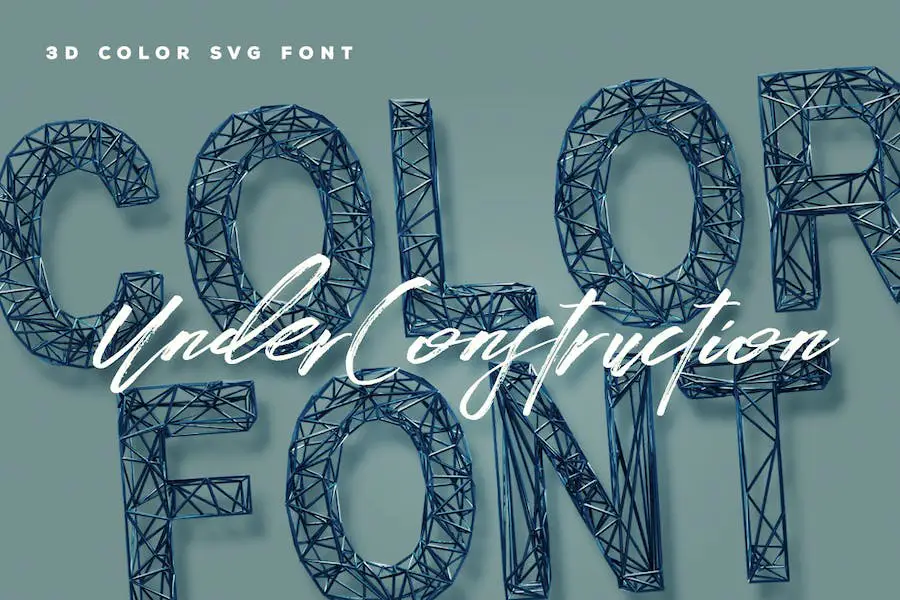
Under Construction adalah font unik dan serbaguna yang dirancang khusus untuk desainer grafis yang mengerjakan proyek terkait konstruksi. Font ini, tersedia dalam format warna dan tipe terbuka SVG, menambahkan sentuhan dinamis dan modern pada desain apa pun.
Dengan bentuk hurufnya yang berani dan menarik perhatian, Under Construction sangat cocok untuk membuat headline, logo, dan signage yang menarik perhatian.
Font ini memberikan kesan kekuatan dan soliditas pada desain Anda, benar-benar menangkap esensi industri konstruksi. Fleksibilitasnya memungkinkannya digunakan dalam berbagai konteks, menjadikannya aset berharga bagi desainer mana pun yang membutuhkan opsi font yang menonjol.
Tukang blok
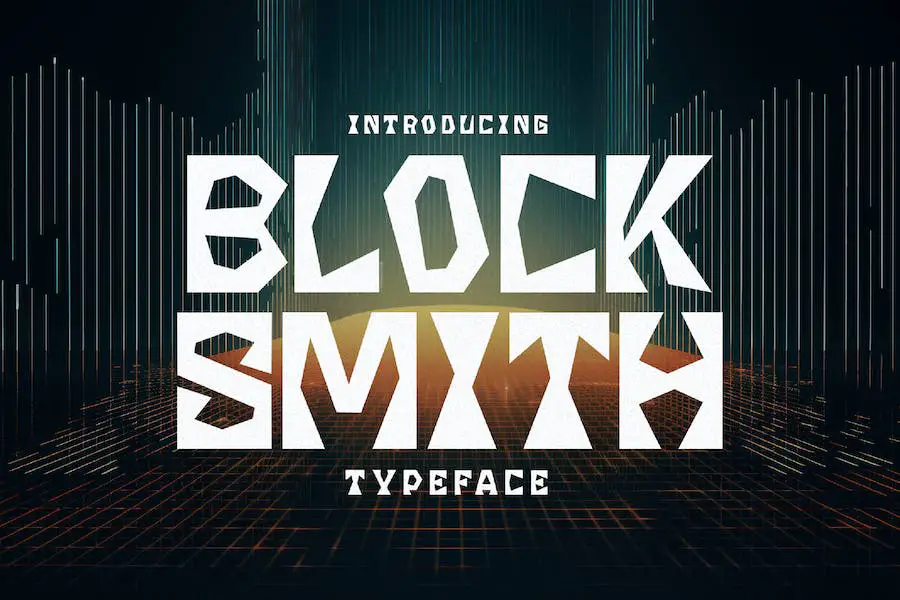
Blocksmith adalah font terbaik untuk desainer grafis yang ingin menyempurnakan desain proyek mereka. Dengan karakteristiknya yang berani dan kokoh, font ini menonjol di dunia tipografi. Ini memberikan kesan kekuatan dan dampak pada proyek apa pun yang digunakannya.
Bentuk Blocksmith yang bersih dan geometris membuatnya sempurna untuk desain bertema konstruksi. Goresannya yang berani dan strukturnya yang kokoh memancarkan kepercayaan diri dan profesionalisme, yang langsung menarik perhatian pemirsa.
Baik itu logo, situs web, atau signage, font ini menambahkan sentuhan kekuatan dan otoritas.
Selain dampak visualnya, Blocksmith sangat serbaguna. Ini dapat dengan mudah ditingkatkan atau diturunkan tanpa kehilangan kejelasannya, memastikan tampilannya bagus pada aplikasi besar dan kecil.
Konstruksi baja
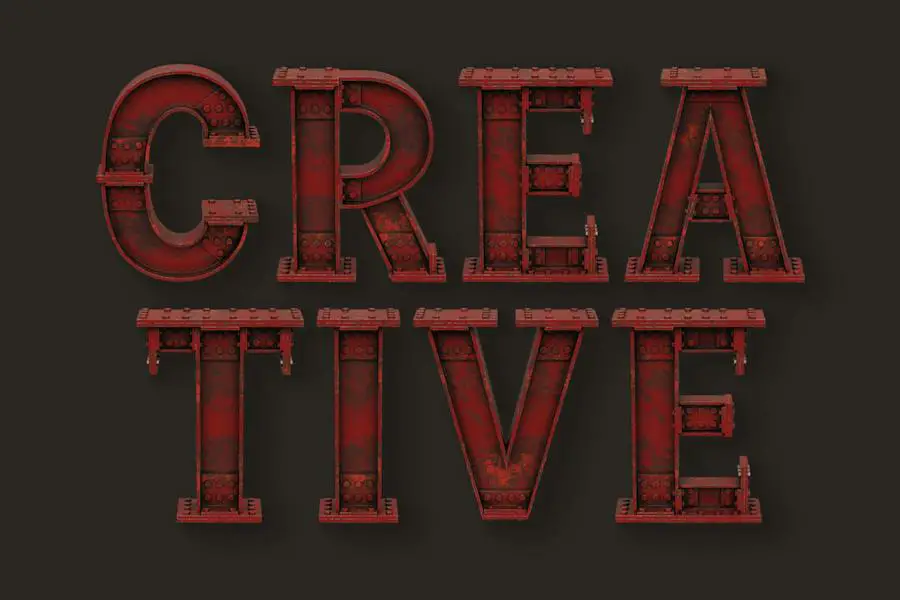
Konstruksi Baja adalah font serbaguna yang menawarkan opsi warna dan tipe terbuka SVG. Dengan desainnya yang berani dan industrial, font ini sangat cocok untuk desainer grafis yang mencari font yang akan menyempurnakan desain proyek mereka.
Atribut font ini mencakup warnanya yang menarik dan garis-garis yang tajam, menjadikannya pilihan yang sangat baik untuk pekerjaan desain yang berhubungan dengan konstruksi. Baik Anda membuat logo, brosur, atau situs web, Konstruksi Baja pasti akan menambah sentuhan profesionalisme dan gaya pada proyek Anda.
Dengan perpaduan unik antara estetika dan fungsionalitas, font ini wajib dimiliki oleh setiap desainer yang ingin tampil menonjol.
Dalam masa pembangunan
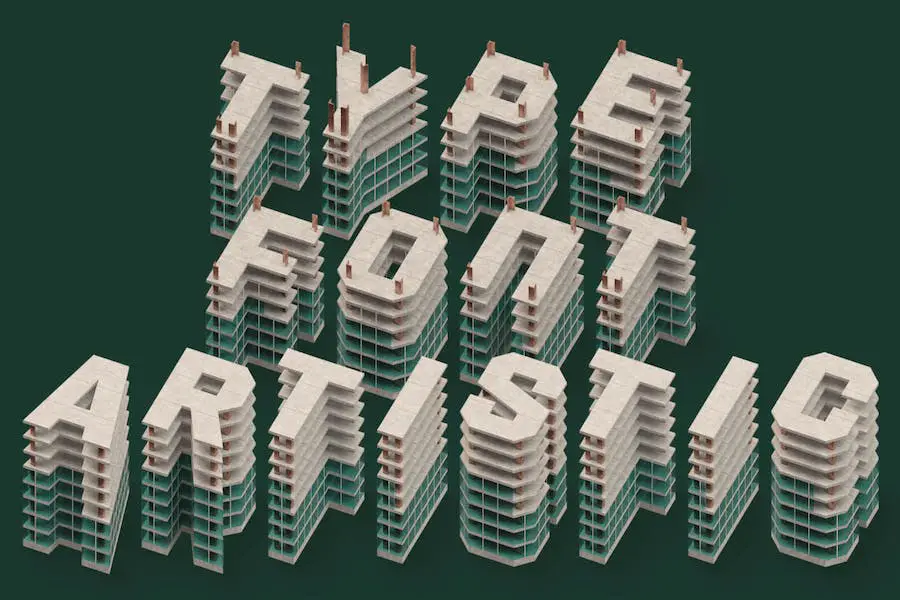
Under Construction adalah font unik dan serbaguna yang menambahkan sentuhan kreativitas dan gaya pada proyek desain grafis apa pun. Dengan huruf tebal dan menarik perhatian, font tipe terbuka berwarna atau SVG ini sempurna untuk menyampaikan kesan kekuatan dan inovasi.
Baik Anda sedang mengerjakan logo, desain situs web, atau proyek visual lainnya, Under Construction pasti akan meningkatkan kualitas pekerjaan Anda dan menarik perhatian audiens Anda.
Atribut font inilah yang membedakannya dari opsi lain di luar sana. Warnanya yang cerah dan format tipe terbuka SVG yang dinamis memungkinkan pengalaman yang benar-benar imersif dan mencolok secara visual.
Setiap huruf dirancang dengan cermat agar menyerupai berbagai elemen konstruksi, seperti balok, baut, dan perancah, menciptakan kesan bangunan dan kemajuan.
Metrisch
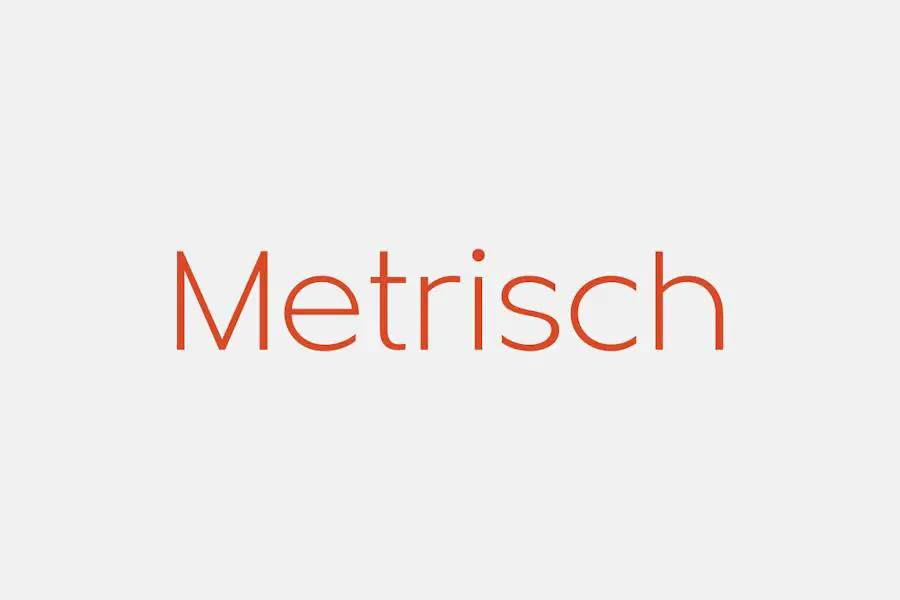
Metrisch adalah keluarga tipe sans serif modern yang menawarkan total tujuh bobot dan huruf miring yang sesuai di setiap bobot. Font serbaguna ini sangat cocok untuk desainer grafis yang ingin menyempurnakan proyek mereka dengan sentuhan ramping dan kontemporer.
Dengan garis-garisnya yang bersih dan tampilannya yang canggih, Metrisch menghadirkan kesan profesionalisme dan keanggunan pada desain apa pun. Ini menawarkan berbagai bobot, memungkinkan desainer untuk menciptakan kontras dan hierarki yang menarik dalam tipografi mereka.
Baik Anda sedang mengerjakan logo, situs web, atau materi cetak, Metrisch siap membantu Anda. Variasi bobot dan huruf miringnya memberi Anda fleksibilitas untuk bereksperimen dan menemukan keseimbangan sempurna untuk desain Anda.
Pasca-beban
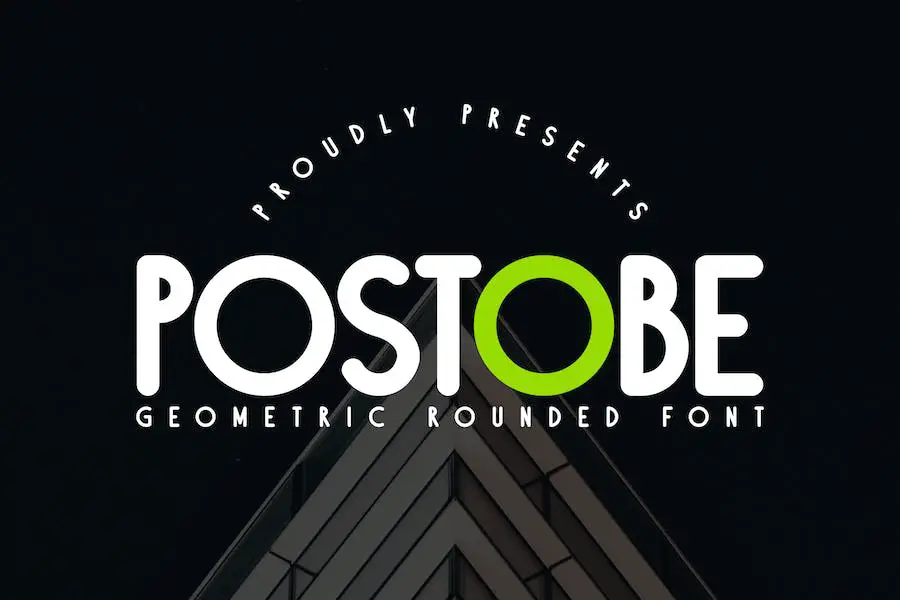
Postobe adalah font serbaguna yang menawarkan berbagai ukuran dan gaya untuk desainer grafis. Dalam koleksi mesin terbangnya, Anda akan menemukan variasi tinggi dan lebar, memungkinkan fleksibilitas desain yang lebih besar. Dengan tiga ukuran berbeda untuk dipilih, Postobe meningkatkan estetika keseluruhan proyek apa pun.
Fitur unik Postobe terletak pada ukuran mesin terbangnya yang disesuaikan. Beberapa mesin terbang sengaja dibuat lebih pendek, sementara yang lain mempertahankan ketinggian standar. Selain itu, mesin terbang tertentu lebih lebar, menambahkan sentuhan dinamis pada tipografi Anda.
Variasi ini memberikan kesempatan bagi desainer untuk bereksperimen dan menciptakan desain visual yang menawan.
Perak Emas
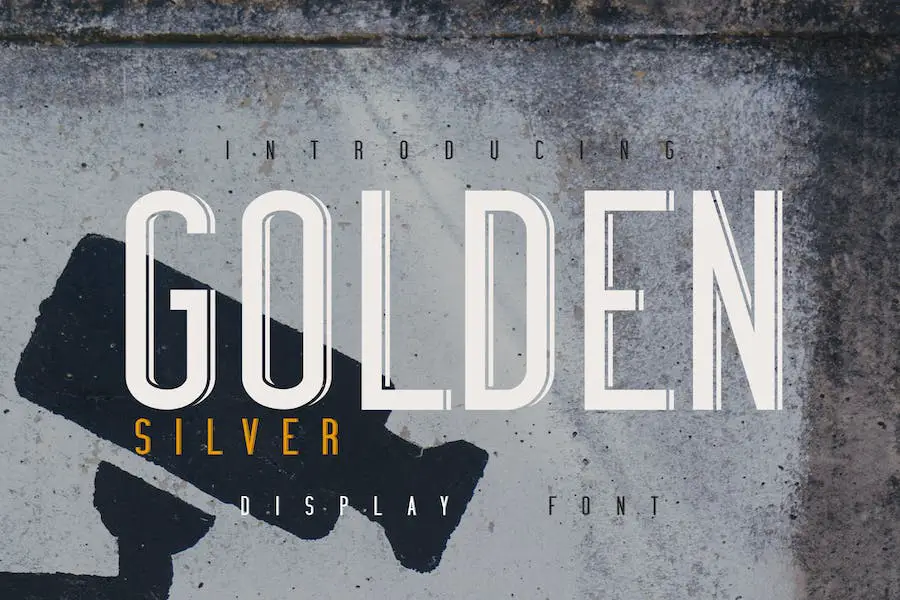
Golden Silver adalah font yang menghadirkan sentuhan keanggunan dan kecanggihan pada setiap proyek desain grafis. Didesain khusus dengan mempertimbangkan konstruksi dan pekerjaan berat, font ini berani dan berani, sama seperti industri yang diwakilinya.
Salah satu fitur menonjolnya adalah sisi khusus seperti bayangan dalam jajaran karakternya, menambahkan elemen unik dan menarik pada desain Anda.
Dengan Golden Silver, Anda dapat langsung meningkatkan proyek Anda dengan memberikan kesan halus dan profesional.
Baik Anda membuat logo untuk perusahaan konstruksi atau merancang materi promosi untuk merek alat berat, font ini pasti akan memberikan kesan mendalam. Penampilannya yang berani dan berwibawa menuntut perhatian serta memancarkan rasa kekuatan dan keandalan.
Teroksia Pro
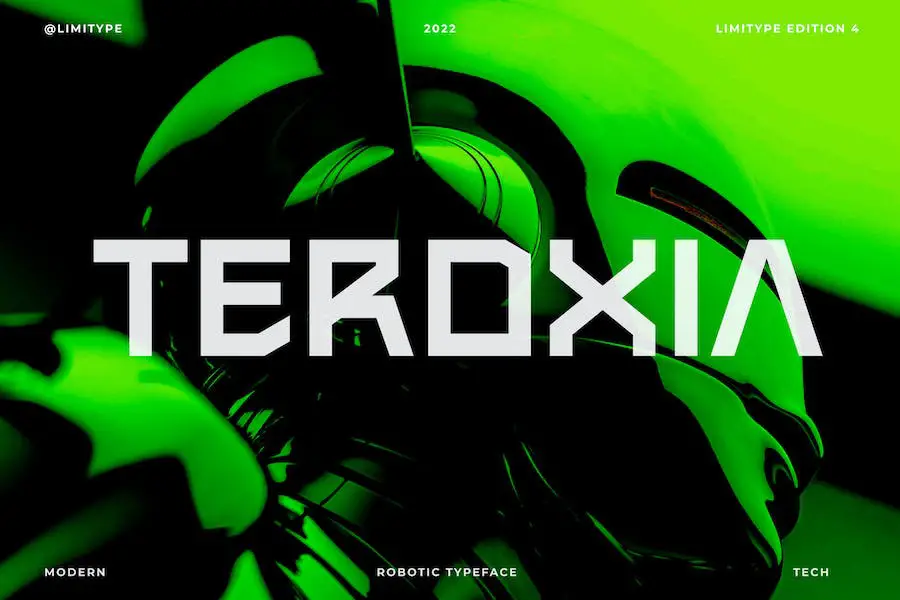
Teroxia Pro adalah jenis huruf unik yang mengambil inspirasi dari bentuk ramping dan kuat yang ditemukan pada robot dan mesin.
Dengan desainnya yang modern dan futuristik, ia menambahkan sentuhan kecanggihan pada setiap proyek desain grafis. Bentuk Teroxia Pro yang tajam dan berani memikat mata dan meningkatkan daya tarik visual secara keseluruhan.
Lengkungan dan konstruksinya yang dibuat dengan cermat menjadikannya font serbaguna yang dapat digunakan untuk berbagai tujuan. Baik Anda sedang mengerjakan logo, poster, atau situs web, Teroxia Pro pasti akan meningkatkan desain ke tingkat yang lebih tinggi.
Astronom
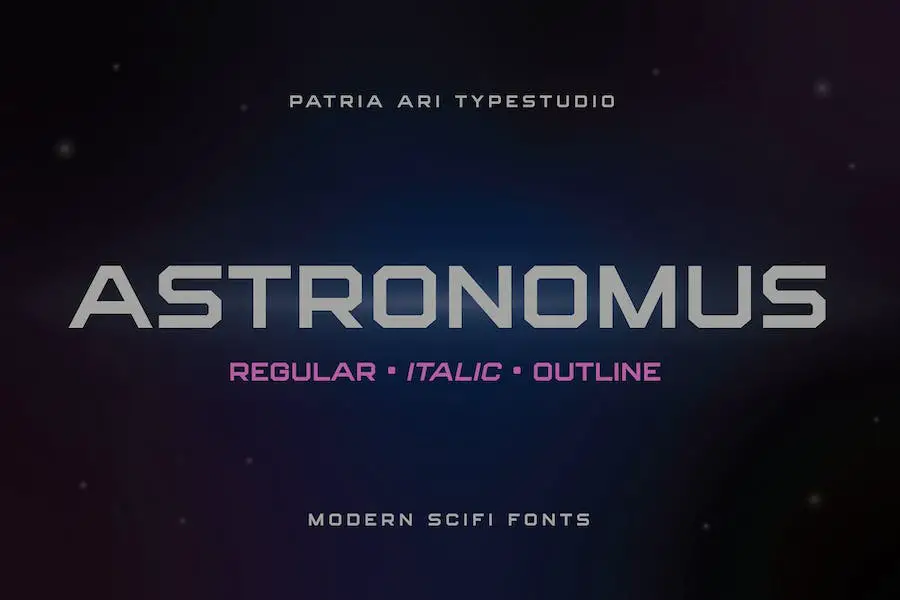
Astronomus adalah font modern berteknologi fiksi ilmiah yang menghadirkan sentuhan futuristik pada desain Anda. Dengan bentuk dan gayanya yang unik, font ini membedakannya dari font tradisional.
Huruf besar dan kecil di Astronomus memiliki variasi yang khas, sehingga menambah unsur kreativitas pada proyek Anda. Tampilannya yang ramping dan modern membuatnya sempurna untuk desain bertema fiksi ilmiah atau teknologi, memberikan kesan mutakhir.
Baik Anda mendesain logo, membuat poster, atau mengerjakan situs web, Astronomus akan membantu meningkatkan proyek Anda dan membuatnya menonjol dari yang lain. Nuansa fiksi ilmiahnya menambah kesan kecanggihan dan futurisme pada desain apa pun.
potongan jalur
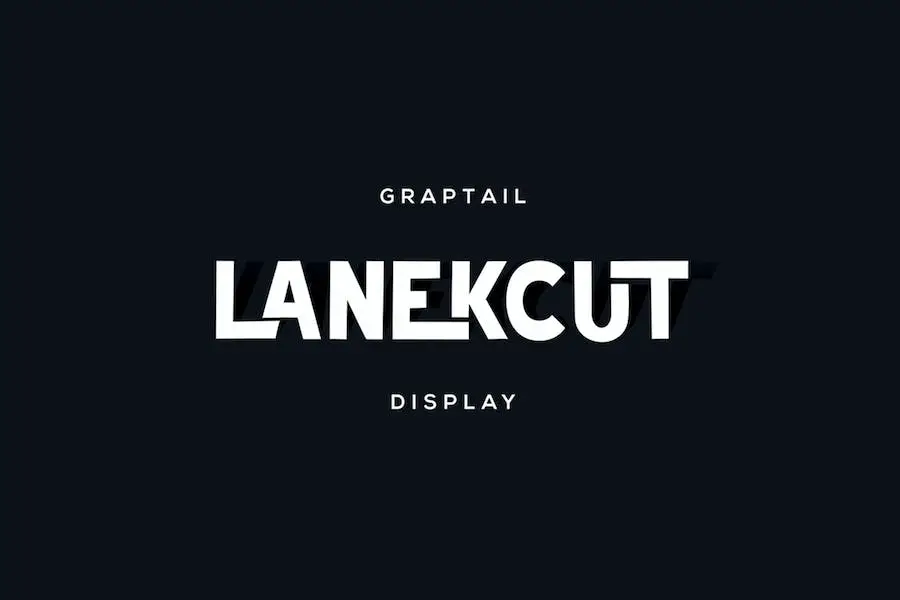
Lanekcut adalah font pengikat yang menggabungkan karakter dan fungsionalitas dengan cara yang unik. Dengan konsep font pengikat, ini memberikan sentuhan khas pada proyek desain apa pun.
Salah satu atribut yang menonjol dari Lanekcut adalah kemampuannya memancarkan karakter. Font ini memiliki kepribadian yang berbeda dan menambahkan sentuhan gaya pada desain apa pun. Baik Anda sedang mengerjakan logo, situs web, atau kemasan, Lanekcut akan membantu menciptakan tampilan yang berkesan dan menarik.
Tapi Lanekcut tidak mengorbankan kegunaan demi gaya. Ini tetap praktis dan mudah dibaca, memastikan pesan Anda tersampaikan secara efektif. Font ini memberikan keseimbangan sempurna antara kreativitas dan fungsionalitas, menjadikannya pilihan serbaguna bagi desainer grafis.
Robinso
Robinson adalah font yang sangat serbaguna yang dapat menyempurnakan desain proyek Anda. Baik Anda sedang mengerjakan branding, kartu nama, poster, logo, majalah, sampul, spanduk, kaos oblong, header, atau bahkan karya seni berskala besar, font ini sangat cocok untuk penggunaan cetak dan layar.
Dengan estetika bersih dan modern, Robinso menambahkan sentuhan kecanggihan pada desain apa pun. Bentuk hurufnya yang ramping dan penuh gaya menciptakan dampak visual yang kuat, membuat teks Anda menonjol dan menarik perhatian. Font ini sangat cocok untuk proyek yang membutuhkan tampilan profesional dan halus.
Salah satu fitur menonjol dari Robinso adalah keterbacaannya yang luar biasa. Setiap huruf dibuat dengan cermat untuk memastikan keterbacaan, bahkan pada ukuran yang lebih kecil. Hal ini menjadikannya ideal untuk proyek di mana Anda perlu menyampaikan informasi dengan jelas dan efektif.
Baik Anda mendesain tata letak majalah atau logo, Robinson akan memastikan pesan Anda mudah dipahami.
Musim panas
Musim panas adalah font tulisan tangan yang menyenangkan dengan konstruksi kokoh yang menambahkan sentuhan pesona pada proyek desain apa pun. Atribut uniknya menjadikannya suatu keharusan bagi desainer grafis yang ingin menyempurnakan proyek mereka.
Dengan Musim Panas, Anda mendapatkan yang terbaik dari kedua dunia: tampilan tulisan tangan dipadukan dengan fondasi yang kokoh. Konstruksinya yang kokoh memberikan kekuatan dan stabilitas pada font, menjadikannya sempurna untuk menyampaikan rasa keandalan dan profesionalisme.
Font ini memancarkan kesan keaslian, seolah-olah ditulis dengan tangan dengan hati-hati dan memperhatikan detail. Garis-garisnya yang halus dan proporsinya yang seimbang membuatnya enak dipandang, sementara konstruksinya yang kuat memastikan keterbacaan dalam berbagai ukuran dan konteks.
Font Konstruksi Gratis Terbaik
Ingin menambahkan sentuhan ekstra kreativitas pada proyek konstruksi Anda? Lihat pilihan font konstruksi gratis terbaik kami. Font ini tidak hanya menarik secara visual tetapi juga sangat serbaguna, memungkinkan Anda meningkatkan desain Anda ke tingkat yang lebih tinggi.
Jangan lewatkan kesempatan ini untuk menyempurnakan proyek Anda – lihat produk berikut di artikel ini!
Konstruksi
Konstruksi adalah font yang dirancang khusus untuk desainer grafis yang ingin menyempurnakan desain proyek mereka. Ini adalah font serbaguna dan bergaya yang dapat digunakan dalam berbagai desain terkait konstruksi.
Dengan garis-garisnya yang berani dan bersih, Konstruksi menambahkan sentuhan modern dan profesional pada proyek apa pun.
Font ini menampilkan huruf-huruf yang kuat dan solid yang memancarkan kesan kuat dan stabil. Baik Anda membuat logo untuk perusahaan konstruksi atau mendesain selebaran untuk proyek bangunan, Konstruksi adalah pilihan yang tepat.
Penampilannya yang berani dan bertenaga langsung menarik perhatian dan memberikan kesan yang kuat.
Garis Konstruksi
Construction Lines adalah font yang dibuat oleh Checkered Ink yang sempurna untuk desainer grafis yang ingin menyempurnakan desain proyek mereka. Font serbaguna ini menambahkan sentuhan unik dan profesional pada desain bertema konstruksi apa pun, menjadikannya menonjol dari pesaing.
Dengan garis-garisnya yang bersih dan tampilannya yang berani, Construction Lines cocok untuk berbagai proyek terkait konstruksi, termasuk logo, data infografis, dan iklan.
Tepian font yang tajam dan kehadiran yang kuat membuatnya menarik secara visual dan mudah dibaca, memastikan pesan Anda dikomunikasikan secara efektif kepada audiens Anda.
Atribut Garis Konstruksi benar-benar menjadikannya pilihan font yang menonjol. Bentuk hurufnya yang kokoh dan berani memberikan kesan keandalan dan kekuatan, yang secara sempurna mencerminkan esensi industri konstruksi.
Font ini juga mempertahankan estetika yang ramping dan modern, memberikan desain Anda keunggulan kontemporer.
Mekanisme
Mechanismo oleh sdotype adalah pilihan font yang fantastis untuk desainer grafis yang ingin meningkatkan desain proyek mereka. Font bertema konstruksi ini menambahkan sentuhan unik dan menghadirkan kesan kekuatan dan presisi pada desain apa pun.
Dengan bentuk huruf yang tebal dan bersudut, Mechanismo sempurna untuk membuat headline, logo, dan signage yang menarik.
Atribut Mechanismo menjadikannya pilihan yang sangat baik untuk proyek desain apa pun. Bentuknya yang berani dan geometris memberikan dampak visual yang kuat, sementara garis-garisnya yang rapi memastikan keterbacaan bahkan pada ukuran kecil.
Elemen khas yang terinspirasi dari konstruksi menambah kesan kecanggihan industri pada desain apa pun, menjadikannya pilihan sempurna untuk proyek terkait konstruksi atau desain apa pun yang bertujuan untuk memberikan kekuatan dan stabilitas.
Txuleta Deco
Txuleta Deco adalah font fantastis yang dapat menyempurnakan desain proyek konstruksi Anda. Dibuat oleh deFharo, atribut unik dan bergaya font ini menjadikannya wajib dimiliki oleh setiap desainer grafis yang ingin menambahkan sentuhan elegan pada karyanya.
Dengan Txuleta Deco, Anda akan memiliki akses ke berbagai fitur yang akan membuat desain Anda benar-benar menonjol.
Garis font yang ramping dan modern memberikan tampilan yang canggih, cocok untuk menampilkan profesionalisme dan kreativitas proyek konstruksi Anda. Desainnya yang berani dan bersih memastikan teks Anda jelas dan terbaca, bahkan pada ukuran yang lebih kecil.
Salah satu fitur menonjol dari Txuleta Deco adalah keserbagunaannya. Baik Anda sedang mengerjakan brosur, atau situs web, font ini akan beradaptasi dengan mulus pada proyek apa pun.
cepat
Fastup adalah font fantastis yang dibuat oleh deFharo yang sempurna untuk desainer grafis yang ingin menyempurnakan desain proyek mereka. Font ini memiliki tampilan ramping dan modern yang menambahkan sentuhan profesional pada desain apa pun.
Garis-garisnya yang bersih dan gayanya yang berani menjadikannya ideal untuk proyek bertema konstruksi. Dengan Fastup, Anda dapat dengan mudah membuat logo, papan tanda, dan materi promosi menarik yang menonjol dari yang lain.
Font ini menawarkan berbagai atribut yang menjadikannya wajib dimiliki oleh desainer grafis. Fleksibilitasnya memungkinkannya bekerja dengan baik dalam ukuran besar dan kecil, memastikan keterbacaan dan dampak visual dalam berbagai aplikasi.
Sifat Fastup yang berani juga menjamin keterbacaan, bahkan dari jarak jauh. Selain itu, desain font yang bersih memudahkan untuk dipasangkan dengan tipografi lain, memungkinkan kemungkinan kreatif tanpa batas.
Lapangan Madison NF
Madison Square NF oleh Nick's Fonts adalah font yang sempurna untuk desainer grafis yang ingin menyempurnakan desain proyek mereka. Font ini memiliki gaya unik dan menarik yang dapat menghadirkan sentuhan kecanggihan pada desain apa pun.
Dengan garis-garis yang bersih dan estetika yang berani, Madison Square NF adalah pilihan yang sangat baik untuk proyek-proyek di industri konstruksi.
Atribut Madison Square NF membuatnya menonjol di antara font lainnya. Bentuk hurufnya yang kuat dan berani menarik perhatian, menjadikannya pilihan tepat untuk judul dan judul. Font ini juga memiliki bentuk geometris yang khas, yang menambah kesan modern dan ramping pada desain apa pun.
Selain itu, Madison Square NF menawarkan beragam bobot dan gaya, memungkinkan desainer bereksperimen dan menemukan yang paling cocok untuk proyek mereka.
Pertanyaan yang Sering Diajukan
Font konstruksi adalah kumpulan tipografi yang dirancang khusus untuk industri konstruksi. Font ini sering kali menampilkan huruf tebal dan kuat yang menyampaikan kesan kuat, tahan lama, dan profesionalisme.
Mereka biasanya digunakan dalam logo perusahaan konstruksi, papan tanda, dan materi pemasaran untuk menciptakan identitas visual yang selaras dengan nilai-nilai industri.
Menggunakan font konstruksi dapat sangat meningkatkan daya tarik visual dan efektivitas merek Anda di industri konstruksi. Font ini membantu menciptakan identitas merek yang kuat dan berkesan yang sesuai dengan target audiens Anda.
Dengan menggunakan font yang disesuaikan dengan industri konstruksi, Anda dapat menyampaikan profesionalisme, kepercayaan, dan keahlian. Selain itu, font konstruksi dapat membantu bisnis Anda menonjol dari pesaing dan memberikan kesan mendalam pada calon klien.
Saat memilih font konstruksi, penting untuk mempertimbangkan faktor-faktor seperti keterbacaan, kepribadian merek, dan kompatibilitas dengan elemen desain lainnya. Carilah font yang mudah dibaca, memiliki tampilan yang kuat, dan selaras dengan nilai merek dan audiens target Anda.
Jangan takut untuk bereksperimen dan mencari masukan dari orang lain untuk menemukan font yang sempurna untuk proyek Anda.
Kesimpulan
Sebagai kesimpulan, kami telah menjelajahi font konstruksi terbaik yang dapat meningkatkan desain proyek Anda secara signifikan.
Dari font yang tebal dan berkesan hingga yang ramping dan modern, selalu ada font untuk setiap proyek konstruksi. Dengan menggunakan font ini, Anda dapat menambahkan sentuhan profesional dan halus pada desain Anda.
Jika Anda merasa artikel ini bermanfaat, pastikan untuk memeriksa blog BetterStudio untuk tutorial dan sumber daya terkait lainnya. Kami secara rutin memperbarui blog kami dengan informasi berguna untuk membantu desainer grafis seperti Anda meningkatkan keterampilan mereka dan tetap mengikuti perkembangan tren terkini di industri.
Ingat, dengan font konstruksi yang tepat, Anda dapat membawa desain Anda ke tingkat yang lebih tinggi dan membuatnya benar-benar menonjol.